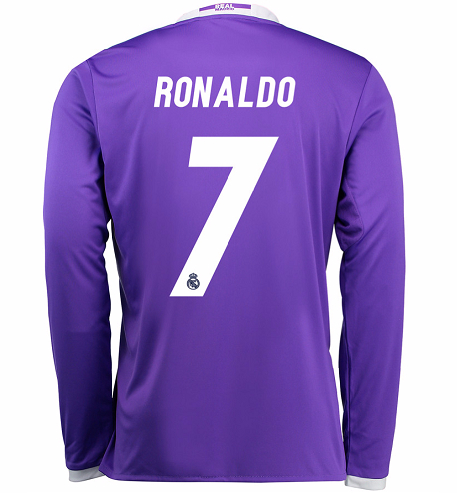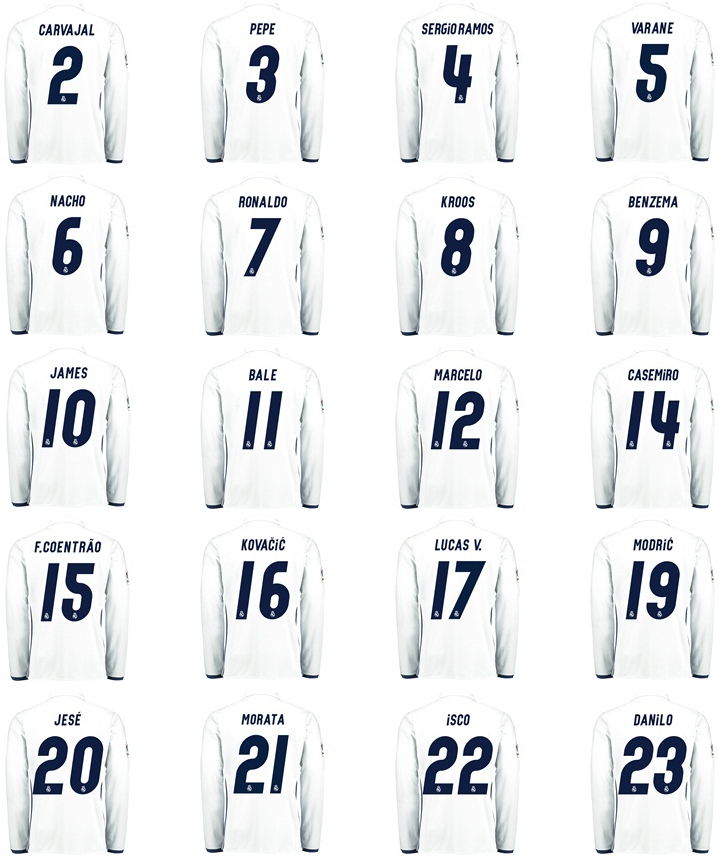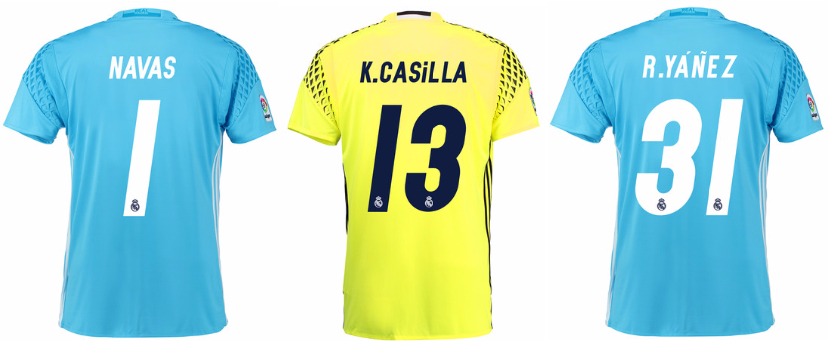
先日、お披露目されたレアル・マドリーの2016-17シーズン用ユニフォーム。ホームは白×青という爽やかかつ上品な仕上がりとなった。
すでにオフィシャルショップでは、新フォントも確認できるので見てみよう。
特徴的だった昨季のものと比べると、モダンでシンプルな書体となっている。紫のアウェイユニだと、こんな感じ。
『footyheadlines』によれば、2005-06シーズンのcursiveフォントからインスパイアされたものだとされている。
確かに面影を感じるような…。